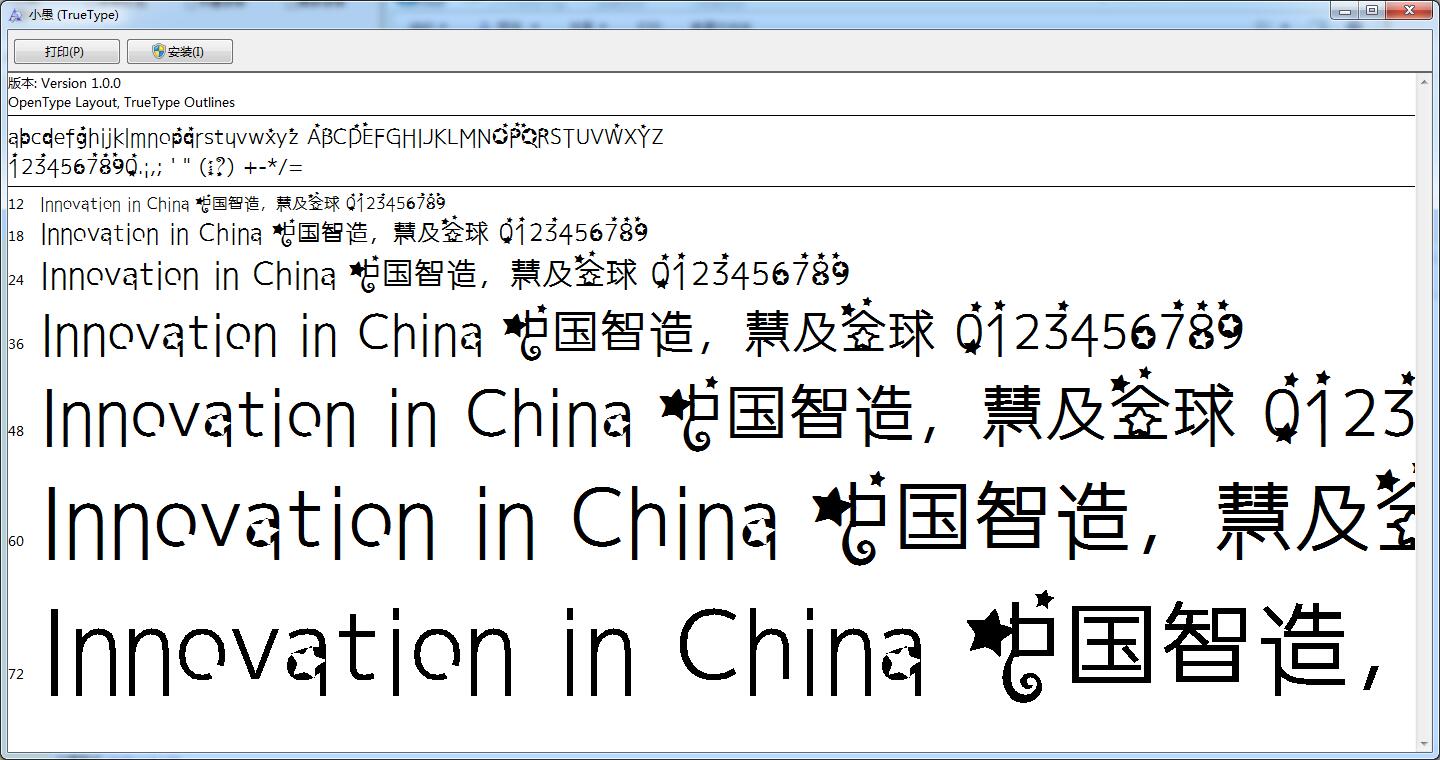
阿苗閃閃字體是一款比較有趣味的字體工具。該字體極具創(chuàng)意和藝術(shù)性,你可以在書寫婚禮邀請(qǐng)函、寫表白信的時(shí)候使用這款字體,可以將文字變得更加有創(chuàng)意哦!歡迎用戶來綠色資源網(wǎng)下載使用!
阿苗閃閃字體是是一款用于閃閃設(shè)計(jì)方面的字體應(yīng)用,這款字體以以黑體字體為原型所創(chuàng)作出的字體,在字體間加入啦星星圖案,使字體具有趣味性,該字體識(shí)別性強(qiáng),整體風(fēng)格出色本作品適用于創(chuàng)意設(shè)計(jì)字體、藝術(shù)設(shè)計(jì)字體、星星設(shè)計(jì)字體!